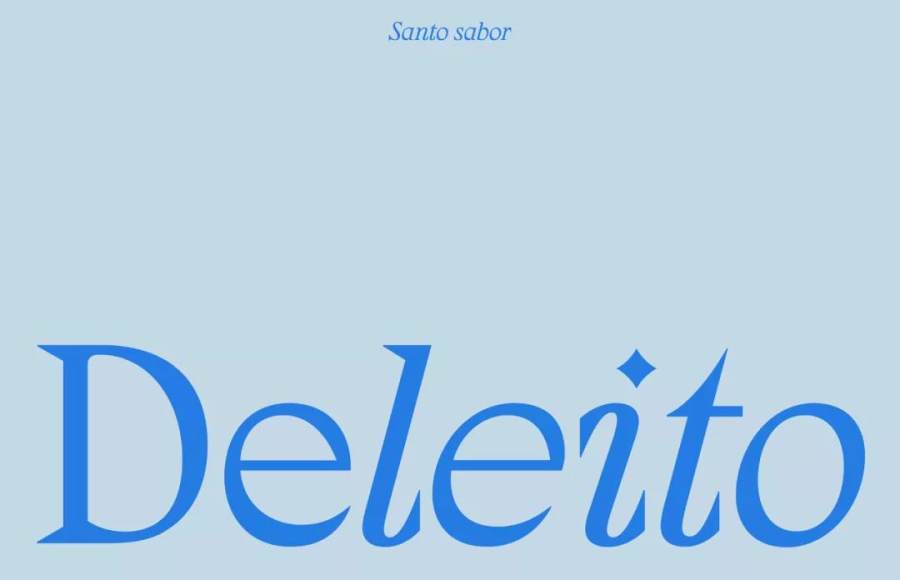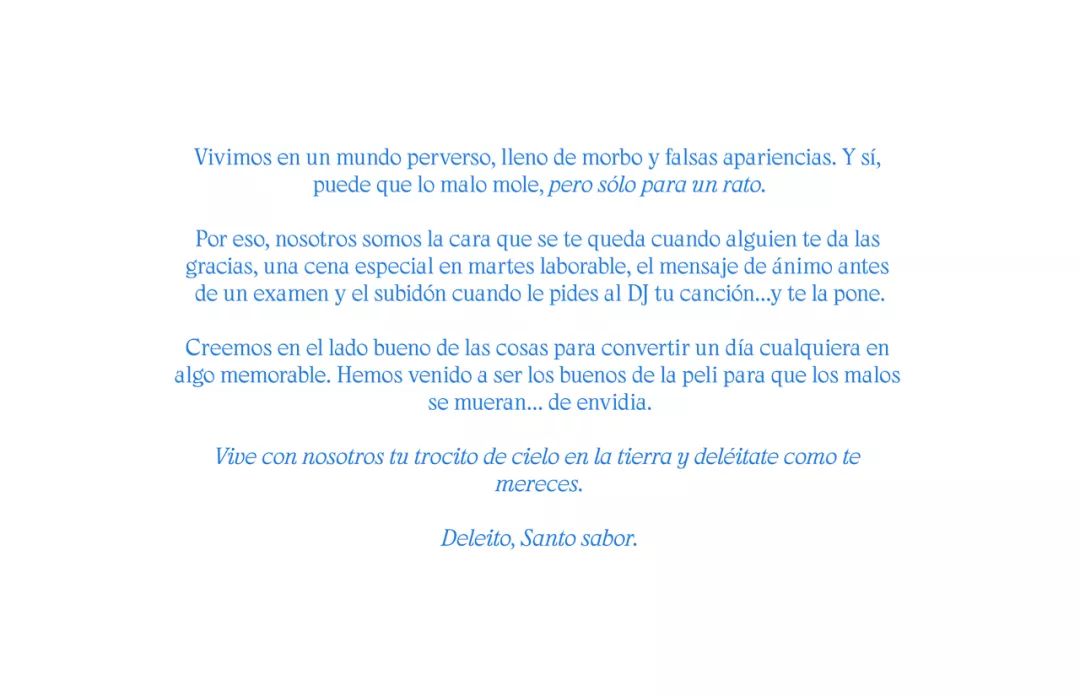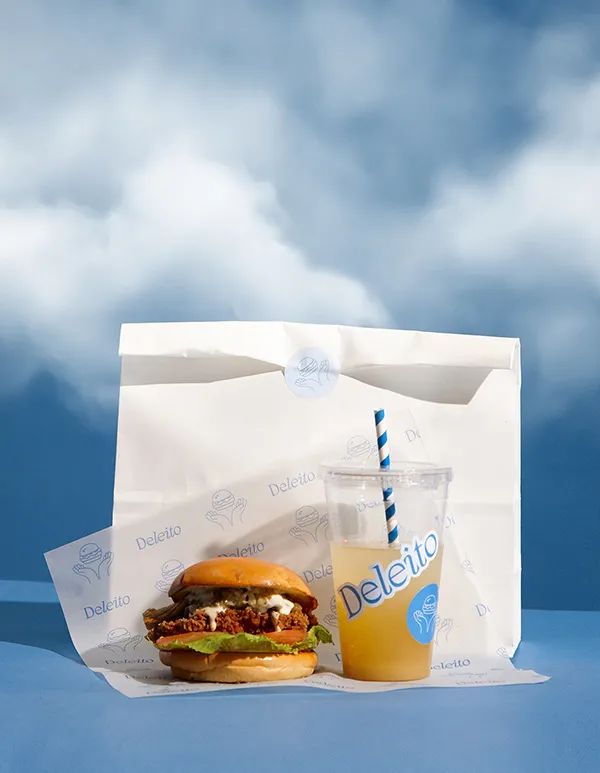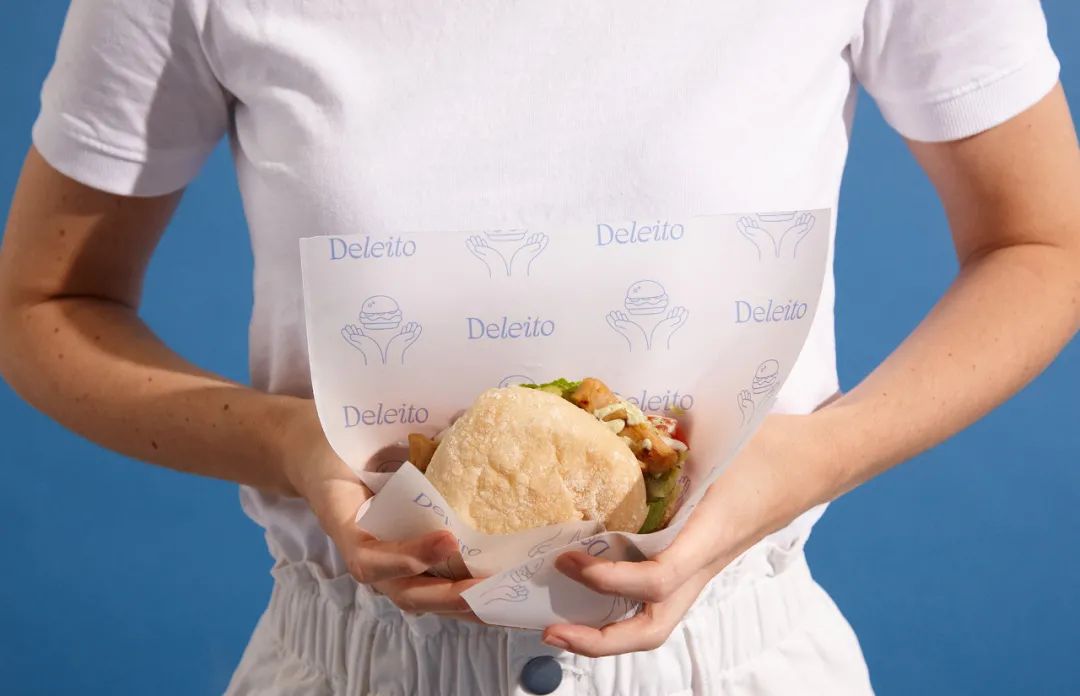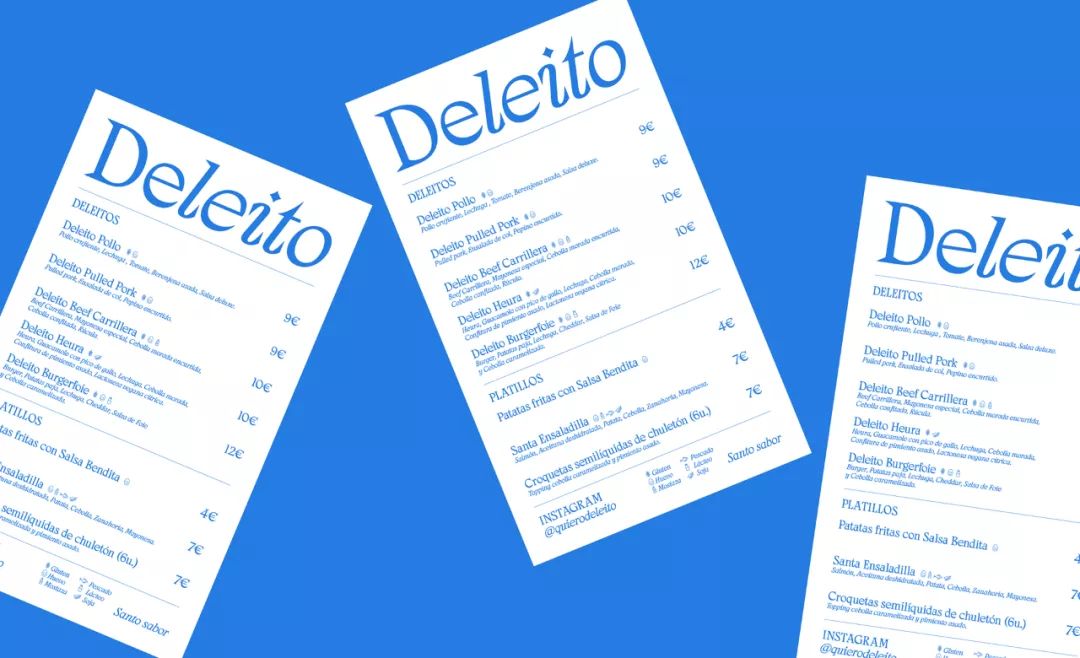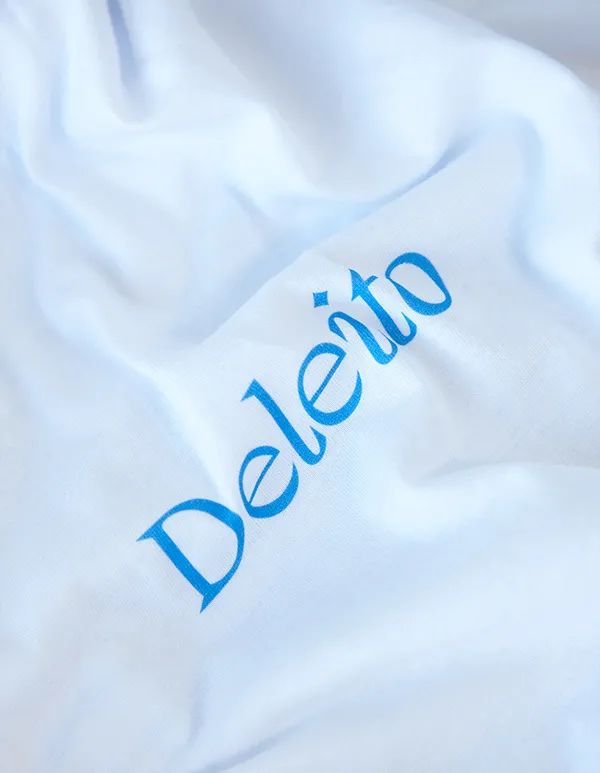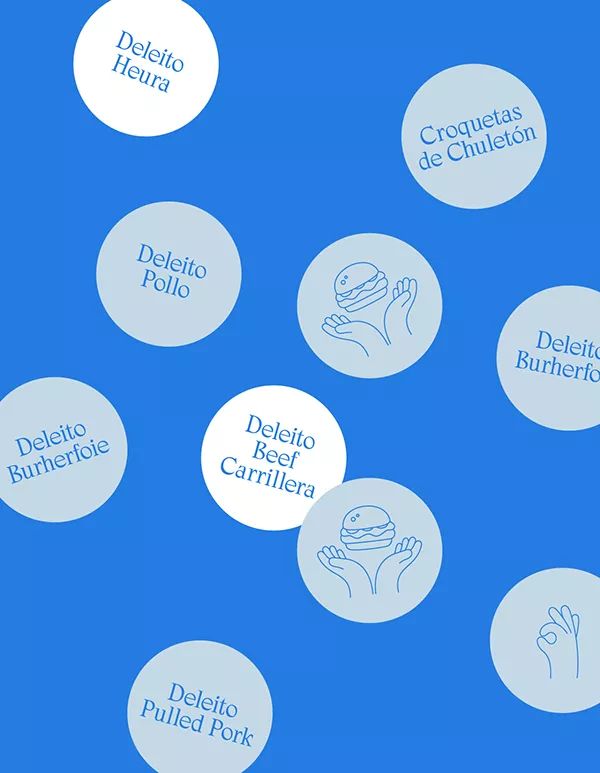
Deleito这个标志的字体设计有点意思
Deleito 是巴塞罗那一家新食品品牌,其寻求通过新的口味和视觉体验来提升品牌影响力。于是委托西班牙 Serena Studio 工作室为其设计了品牌相关视觉工作。
其品牌标志字体设计也有点意思。
第一个字母大写,第二个字母“e”小写,其余的小写并斜着,两个“e”与其中间的“l ”形式了视觉上的对比。